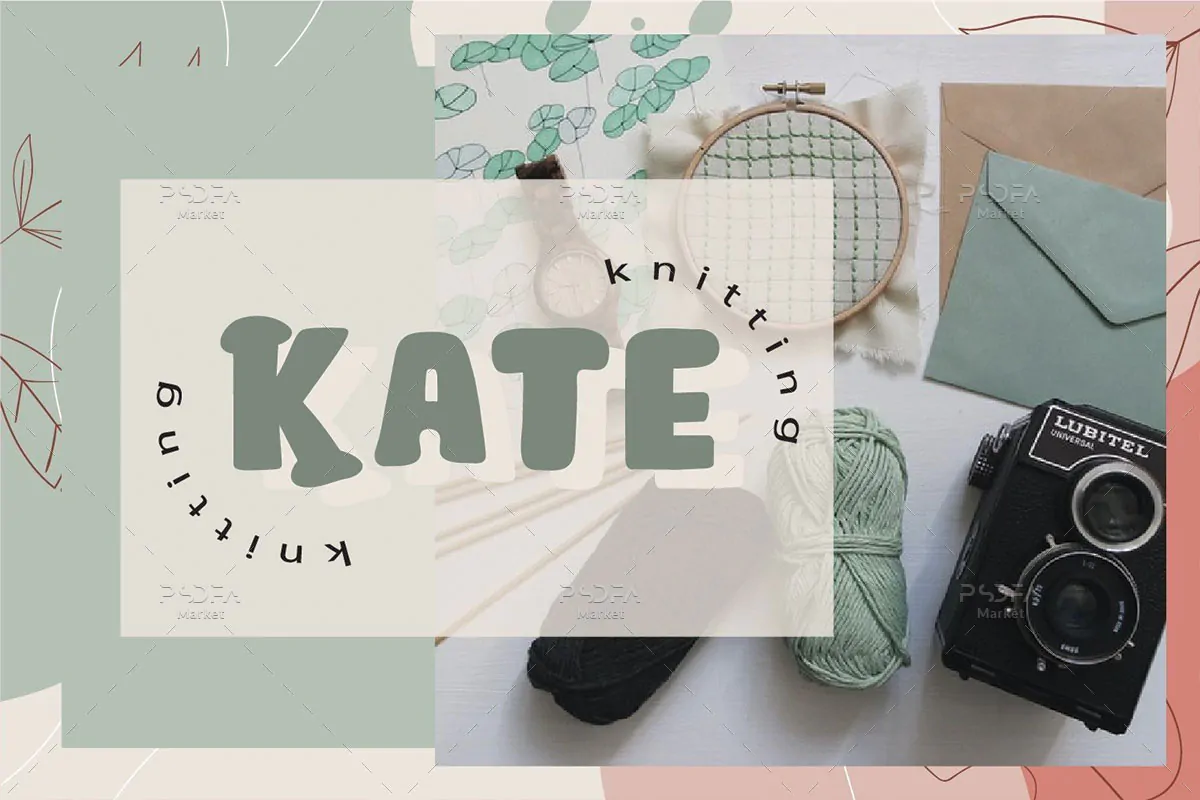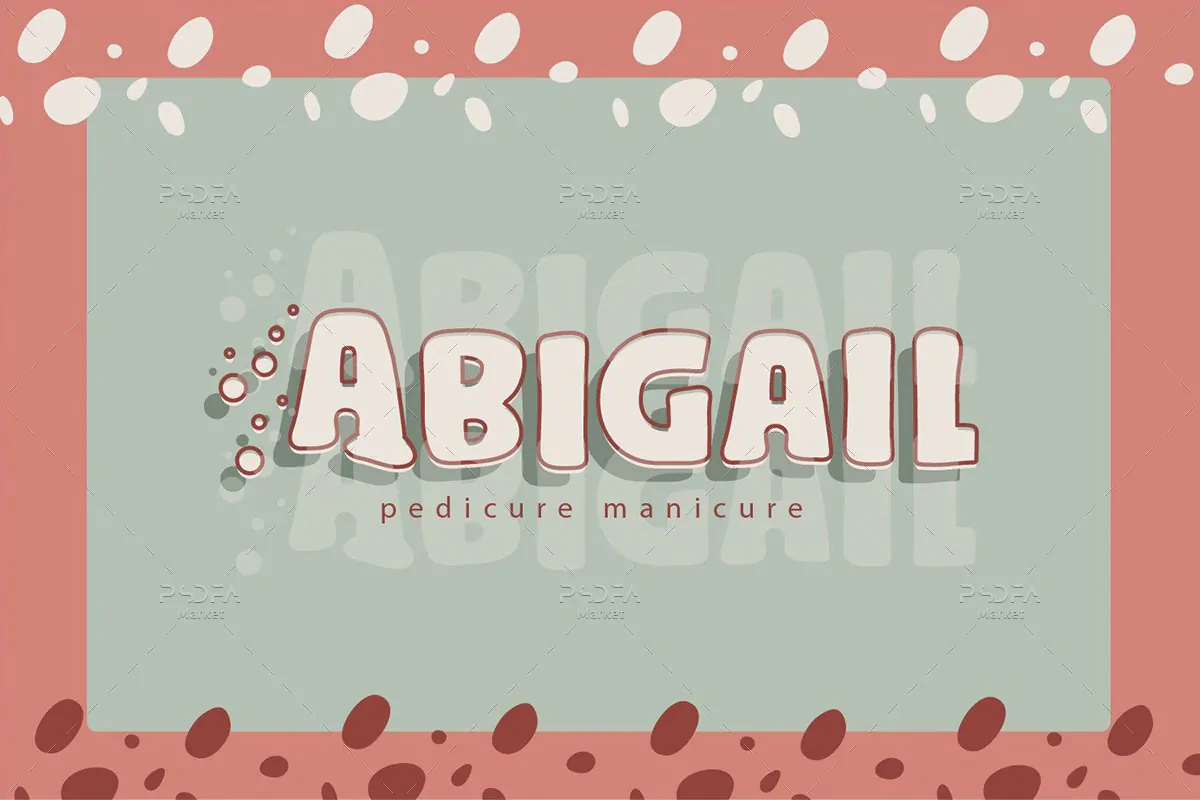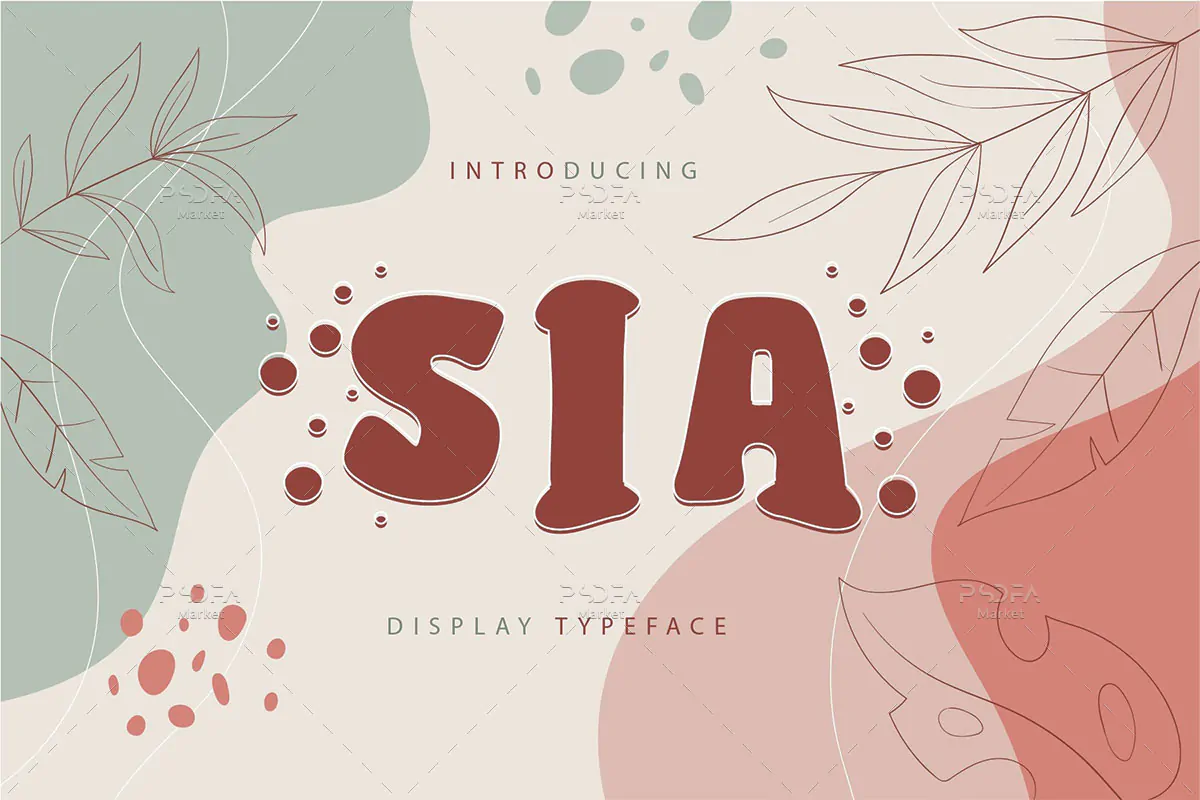
فونت بامزه و جالب حباب دار Sia
فونت بامزه و جالب
فونت بامزه و جالب حباب دار Sia یک قلم نمایشی انگلیسی فوق العاده زیبا است که مناسب برای استفاده در پروژههای گرافیکی مختلف میباشد. فونت Sia با وزن معمولی و با سبک حبابی طراحی شده است که میتوانید از آن در طراحی انواع پوستر، بنر، طرحهای فانتزی، کارتونی و کودکانه، بسته بندی محصولات، لوازم التحریر و … استفاده کنید.